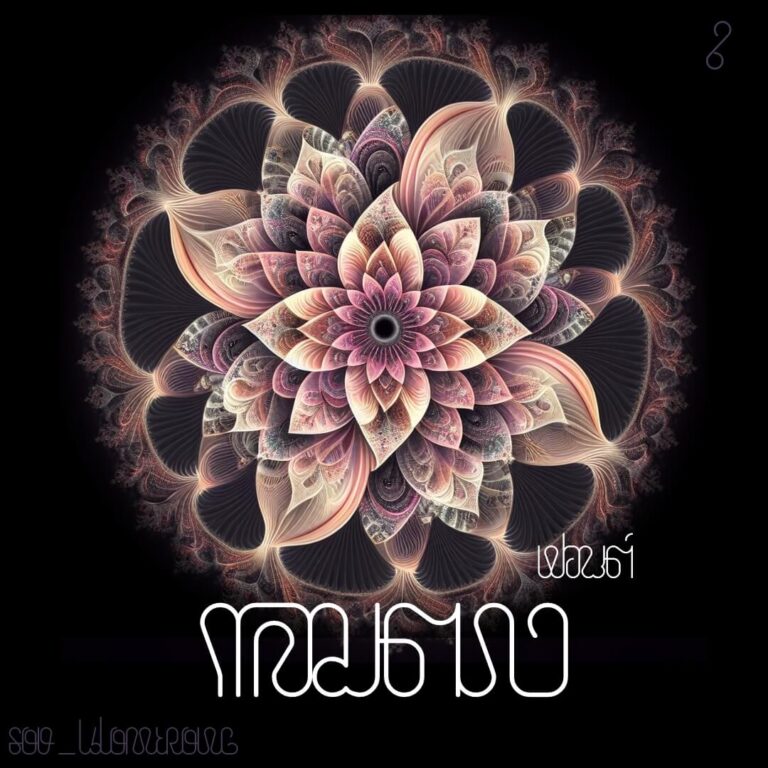
กระเบื้อง (SOV_KraBuang)
ฟอนต์กระเบื้อง – เริ่มต้นที่ 4 กลีบดอกไม้ ลายประจำยาม ลองทำตัว ก.ไก่ ข.ไข่ ฃ.ฃวด หมุนไปหมุนมา ปรับนิดปรับหน่อย… มาเว้ย! ด้นจนจบ แล้วย่อขนาดแต่ละชิ้นนิดนึงกลายเป็นกระเบื้องโมเสก ใช้เป็นโลโก้น่าจะเหมาะกว่า (เพราะอ่านยาก)